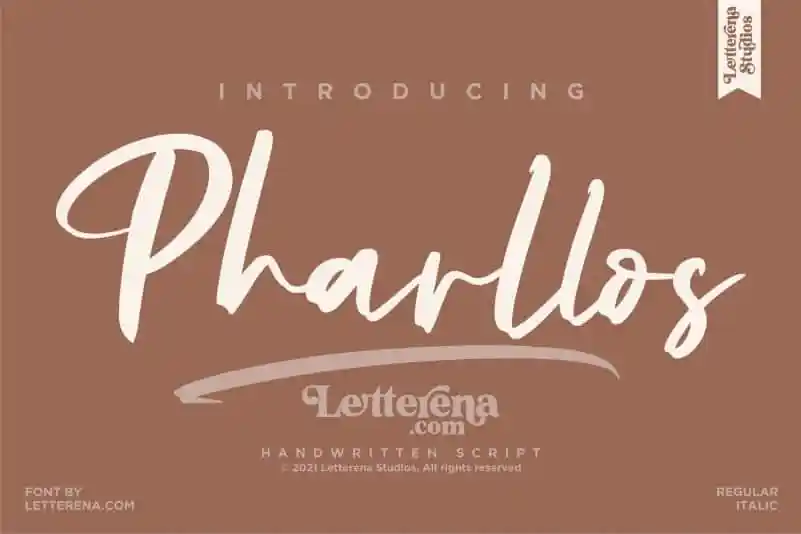
Pharllos Brush Font – Download Grátis
A Fonte Pharllos Brush é uma obra-prima para aqueles que buscam um toque romântico no design de seus projetos. Especialmente criada por Letterenastudios, esta fonte escritura é perfeita para uma infinidade de ideias gráficas. Suas linhas fluidas e detalhes suaves permitem um uso versátil em variedades de projetos, como logotipos, criações de marcas, designs de mobília, embalagens de produtos, capas de livros, cartões de nome, convites, cartões de agradecimento, etiquetas e até mesmo fotografias. Pharllos Brush é uma fonte que traz elegância à sua obra, tornando-a ainda mais sofisticada e personalizada. Seja em um projeto exclusivo ou em qualquer outra tarefa que exige uma assinatura de estilo script, esta fonte oferece o toque final perfeito para suas criações.